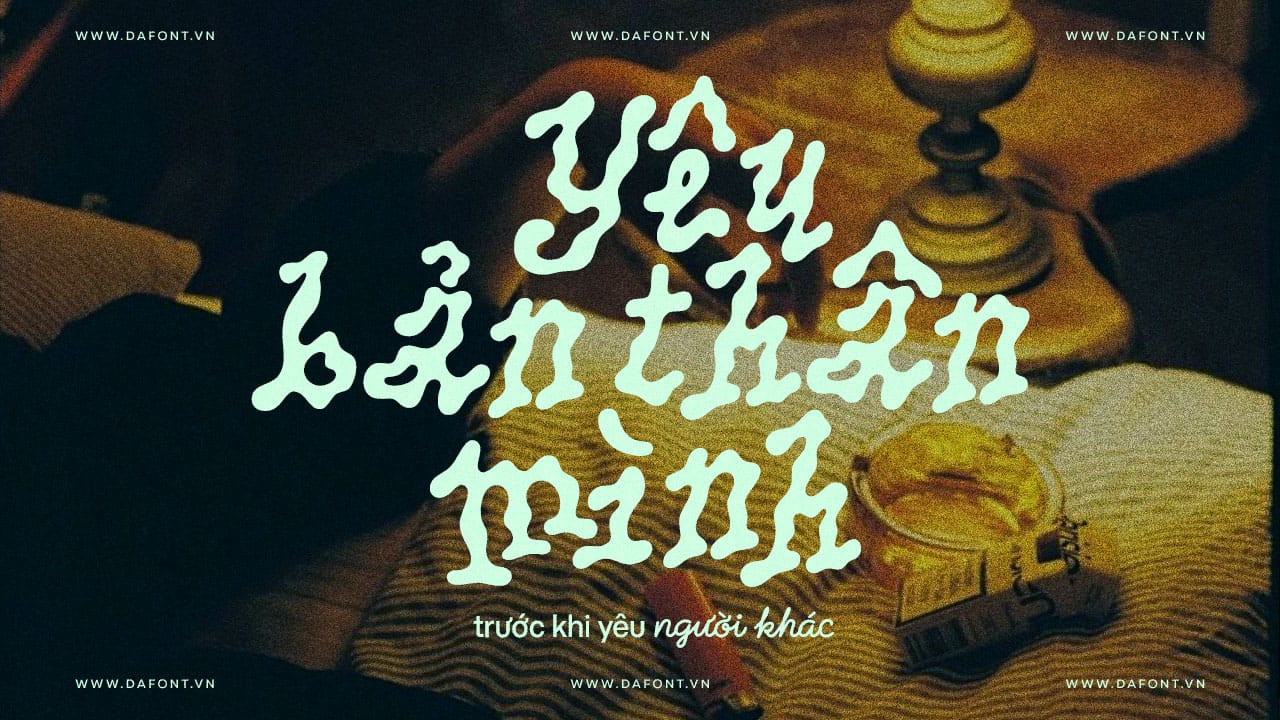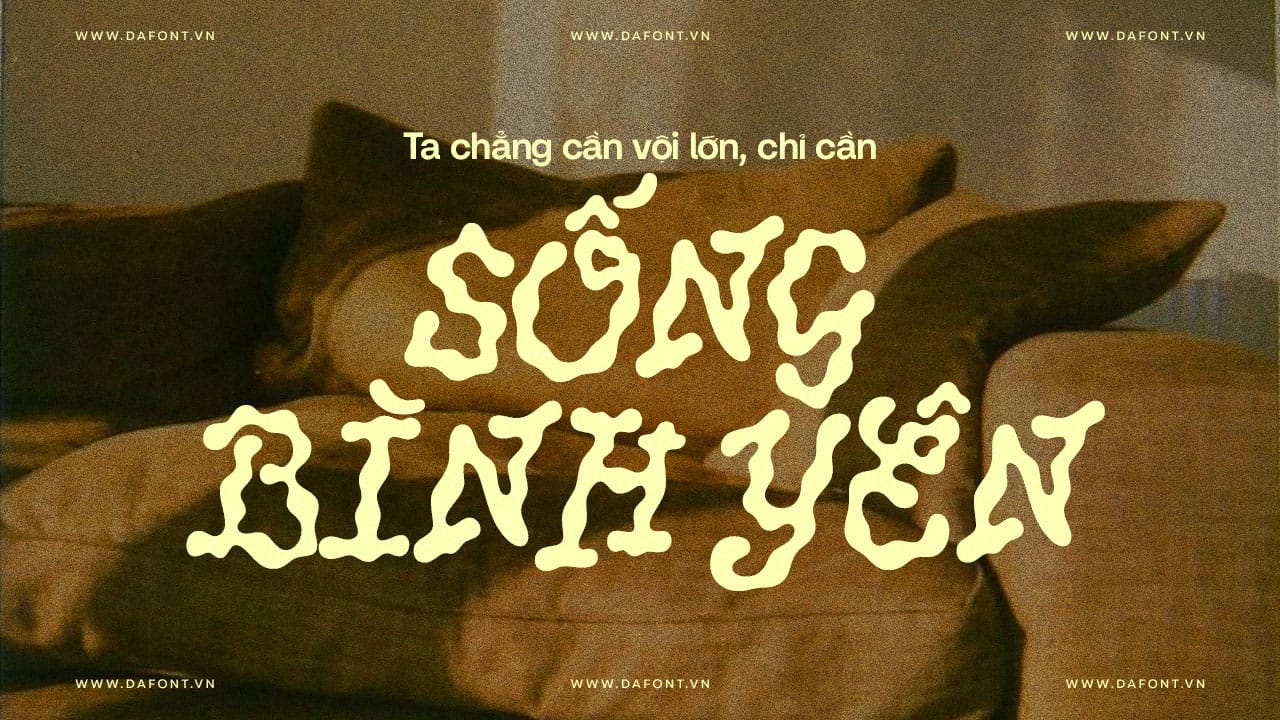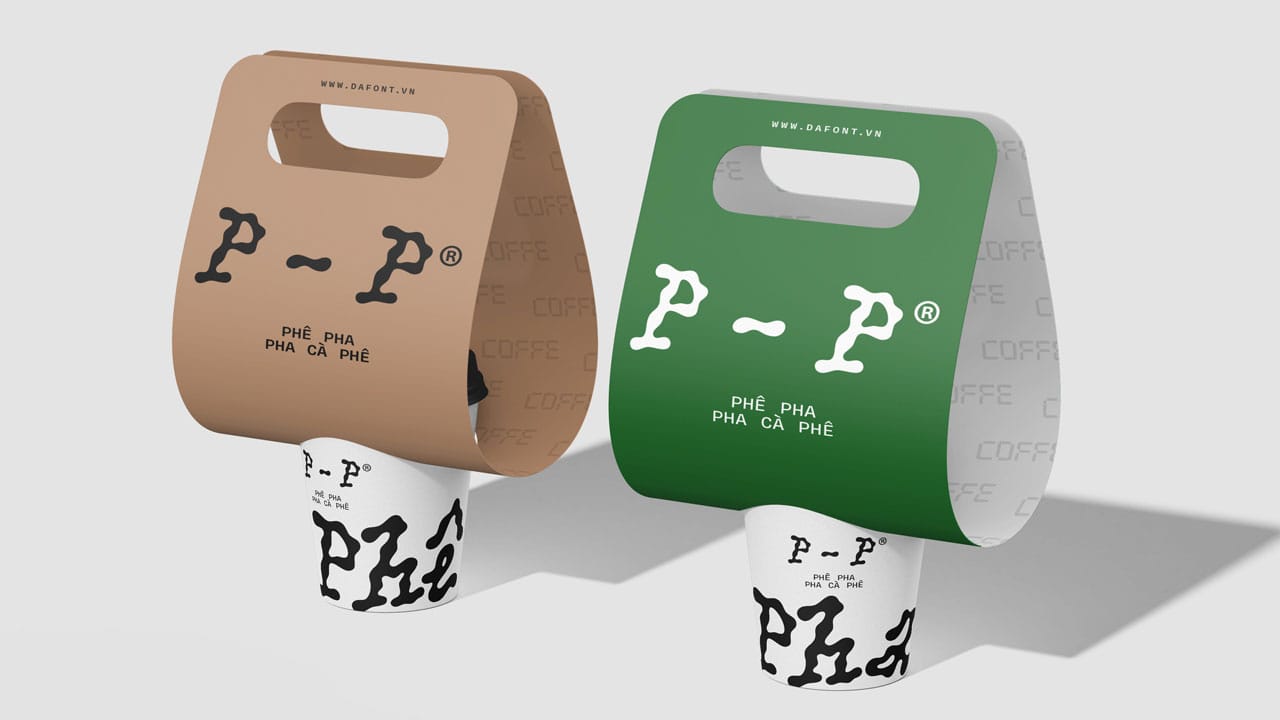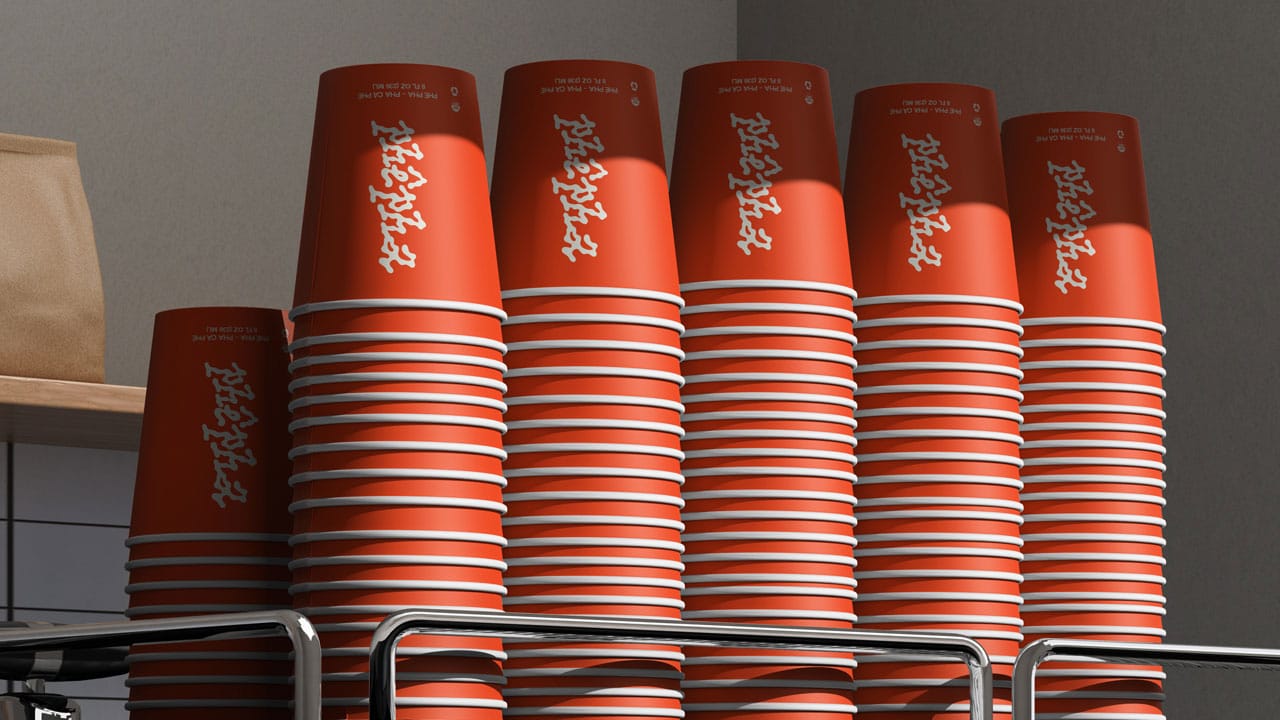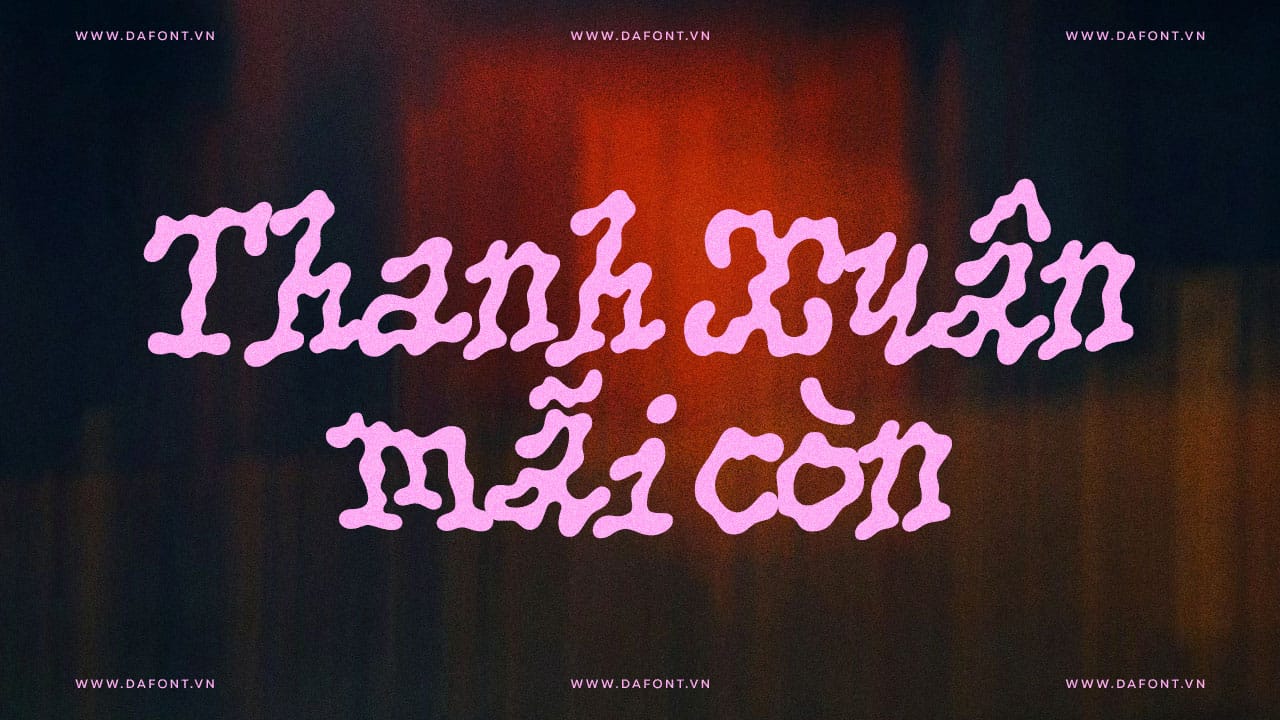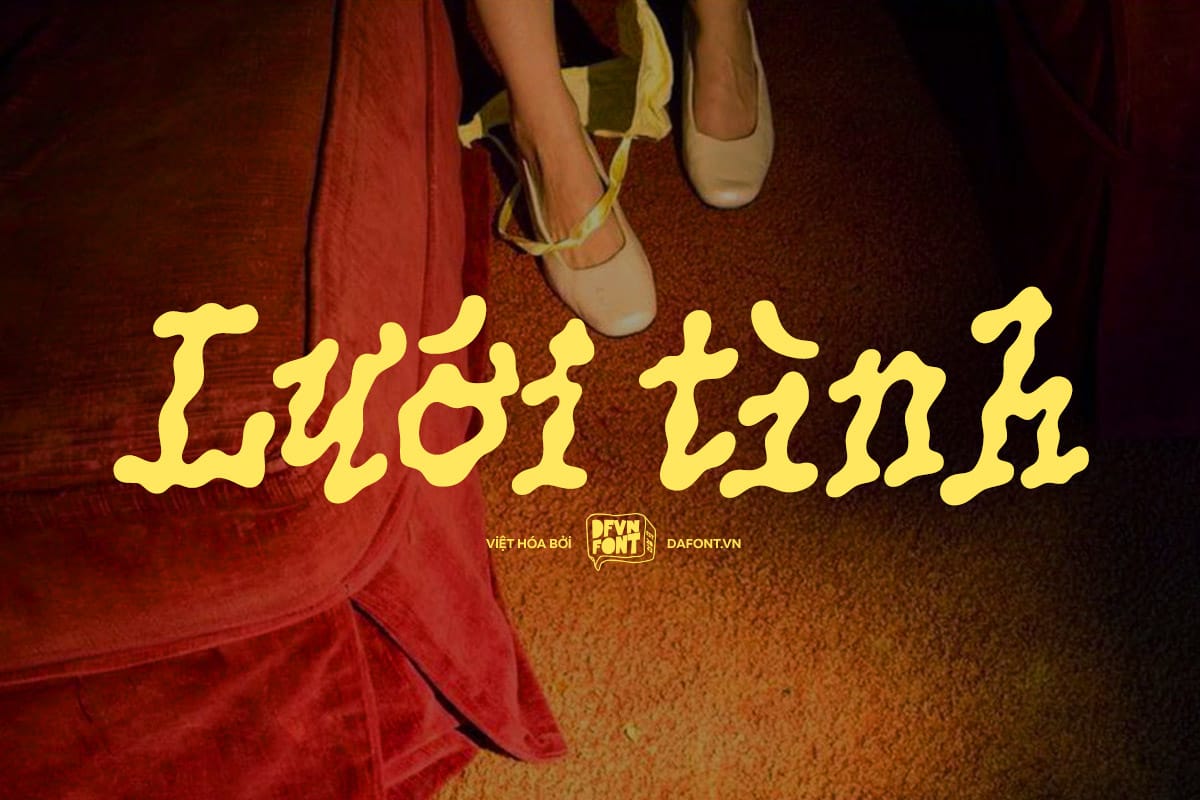
Font Việt hóa DFVN PicNic là một kiểu chữ serif mang phong cách organic và tự nhiên, lấy cảm hứng từ thiên nhiên và những khoảnh khắc bình dị của cuộc sống. Với các nét chữ mềm mại, uyển chuyển và tinh tế, PicNic rất phù hợp cho thiết kế thương hiệu, bao bì, poster hay các dự án sáng tạo mang hơi thở thủ công, mộc mạc.
Cảm hứng thiết kế của PicNic font xuất phát từ những hình ảnh gần gũi, thơ mộng: quỹ đạo của một giọt nước lăn trên khăn trải bàn dầu, bóng lá cây in trên vải nằm trên cỏ, hay đường đi chính xác của một con kiến hướng tới miếng dưa hấu. Những yếu tố này nhằm tái hiện trải nghiệm giác quan của một buổi picnic vui vẻ cùng bạn bè, mang đến sự hoang dã, thơ ca và bucolic (mô tả cảnh quê hương yên bình).
Đặc điểm nổi bật của font PicNic
DFVN PicNic font nổi bật với thiết kế hữu cơ (organic typeface), không theo lối cứng nhắc mà tràn đầy sự linh hoạt và vui tươi. Dưới đây là những tính năng chính khiến font chữ PicNic trở thành lựa chọn yêu thích của các designer:
- Ligatures ngữ cảnh và Inclusive ligatures: Font tự động thay thế midpoint (dấu chấm giữa) bằng các ligatures thông minh, tạo nên dòng chữ mượt mà và tự nhiên. Ví dụ: Các ligatures cơ bản như “bb”, “ct”, “fl”, “ques”, “rss”; ligatures viết hoa như “C FU”, “ŒU”; và inclusive ligatures đặc biệt cho từ như “ICE”, “ices”, “é”, “i·e”.
- Một style duy nhất: Với 1 kiểu regular, font dễ dàng kết hợp trong các dự án đa dạng, từ in ấn đến digital.
- OpenType features: Hỗ trợ đầy đủ ligatures, diacritics (dấu phụ), giúp font hoạt động mượt mà trên các phần mềm như Adobe Illustrator, InDesign hay Figma.
- Thiết kế hữu cơ (Organic typeface): Các đường nét mềm mại, gợi cảm giác tự nhiên, lý tưởng cho nội dung mang tính kể chuyện hoặc cảm xúc.
Ứng dụng và gợi ý sử dụng trong thiết kế
Khi nào nên chọn DFVN PicNic
- Thiết kế thương hiệu mang hướng tự nhiên, handmade, organic: vì chất lượng chữ mềm mại và hơi “ngẫu hứng” nên rất phù hợp.
- Bao bì sản phẩm, nhãn mác, poster sự kiện ngoài trời, flyer picnic, café sân vườn, lifestyle…
- Tiêu đề (heading) hoặc tên thương hiệu, vì chỉ có một style nên không khuyến nghị sử dụng cho văn bản dài chỉn chu.
Gợi ý sử dụng trên website và in ấn
- Trên web: Bạn có thể kết hợp thêm với font sans serif đơn giản để đoạn văn bản dài, còn DFVN PicNic dùng cho tiêu đề.
- Trên in ấn: Với kích thước lớn (poster, banner) sẽ nổi bật tốt nhờ đường nét đặc biệt. Với size nhỏ hơn, cần kiểm tra độ rõ nét.
- Kết hợp font: Vì DFVN PicNic có nét khá “tự do”, bạn nên cân nhắc pairing với font đơn giản – ví dụ sans serif có độ thoáng cao để cân bằng.